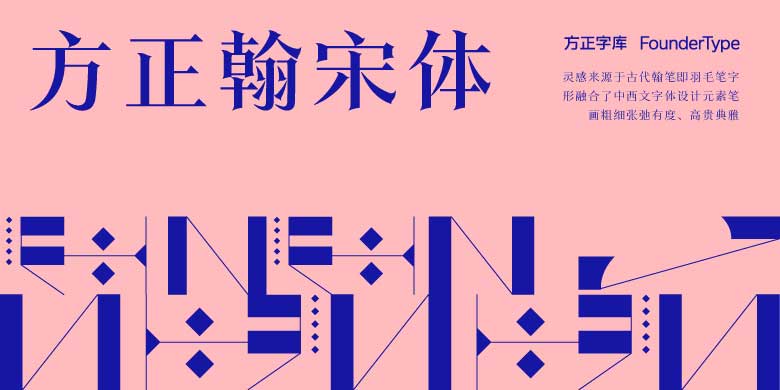
方正翰宋体家族
方正翰宋体家族,这款字体结构工整、笔画清晰,兼顾美观与易读性,适用于标题、正文、海报、包装、LOGO 等多种场景。字形优雅稳定,风格百搭耐看,适配日常排版与创意设计,让文字呈现更舒适、更具质感。方正翰宋体家族一笔一画,皆是细节,以均衡的比例、流畅的线条打造舒适视觉体验,字形端正大气,风格简约现代。无论是商业设计、品牌宣传还是日常排版,都能轻松驾驭,让文字更有格调与力量。方正翰宋体家族字体下载。
翰宋体的灵感来源于古代翰笔,即羽毛笔。字形融合了中西文字体设计元素,在传统的宋体基础上,加入了造型感的装饰,笔画粗细张弛有度,给人以典雅时尚、耳目一新之感。 方正翰宋体家族包含8种字重,适合于标题排版以及时尚、女性类的包装宣传使用。